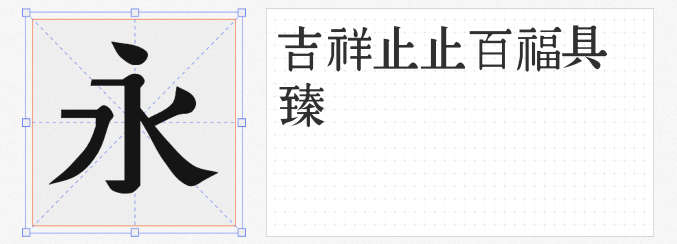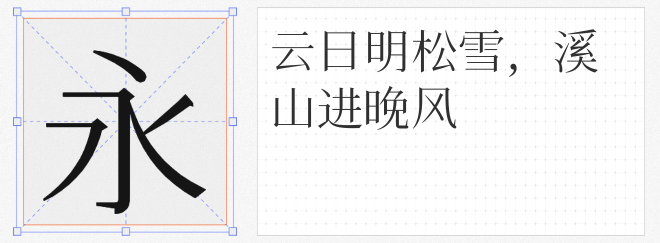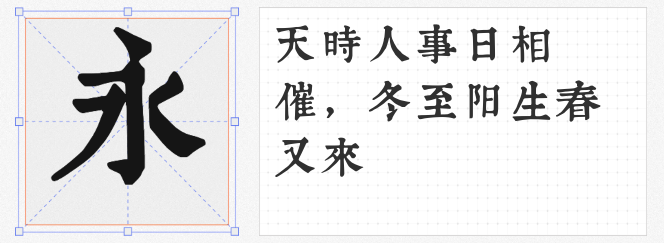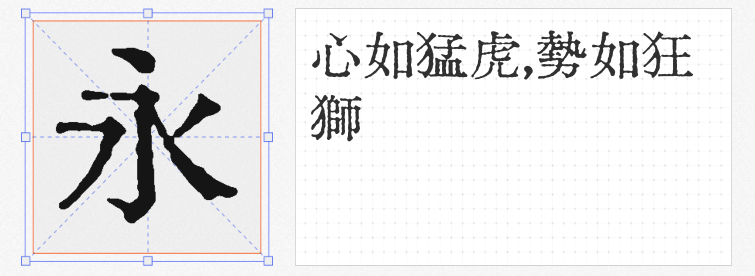
当设计需要唤醒历史记忆时,复古字体便是穿越时空的钥匙。以下四款免费可商用的复刻字体,以铅印质感与古籍韵味,为现代设计注入沉淀百年的文化基因。
1.飞花宋体
脱胎于日文字体“花园明朝”,飞花宋体经过本土化改造,成为简体中文语境中的复古明珠。其笔画末端保留宋体特有的“喇叭口”装饰,横竖转折处却融入手写体的自然弧度,既存传统书卷气,又具现代设计感。适合需要兼具文化厚度与阅读舒适度的书籍装帧、文化海报等场景。
2.汇文筑地五号明朝体
由汉字复兴者天王帝廷匠心打造,这款字体复刻了20世纪铅印古籍的神韵。字面结构紧凑如铸铁,笔画边缘略带手工雕琢的毛糙感,仿佛能嗅到油墨与纸张交织的陈旧气息。其免费商用的属性,让独立设计师也能轻松还原民国文献、老商标等历史风格设计。
3.同文新字典体
从日本活版印刷范本《同文新字典》中涅槃重生,这款字体凝固了江户时代的文字美学。笔画粗细对比强烈,起收笔处多见锐角装饰,竖笔末端常有飘逸的“燕尾”形态,既有字典体的严谨骨架,又带手写体的灵动温度。适用于需要异域复古感的设计,如日式料理店招牌、历史题材文创。
4.润植家康熙字典美化体
以《康熙字典》为蓝本优化而来,这款字体在保留古籍方正骨架的同时,对笔画衔接处进行现代化柔化处理。字面饱满如篆刻,却无生涩之感,尤其适合作为标题字横亘于海报之上,既能彰显文化底蕴,又确保屏幕显示的清晰度。其百搭属性,让传统与现代设计场景皆可从容驾驭。
这四款字体如同装帧精美的古籍善本,让设计师无需穿越即可触摸历史的肌理。从铅印时代的机械美学到手工活版的温度残留,它们以数字化形态延续着文字的文化生命,为免费商用设计打开了一扇通往时光深处的窗。